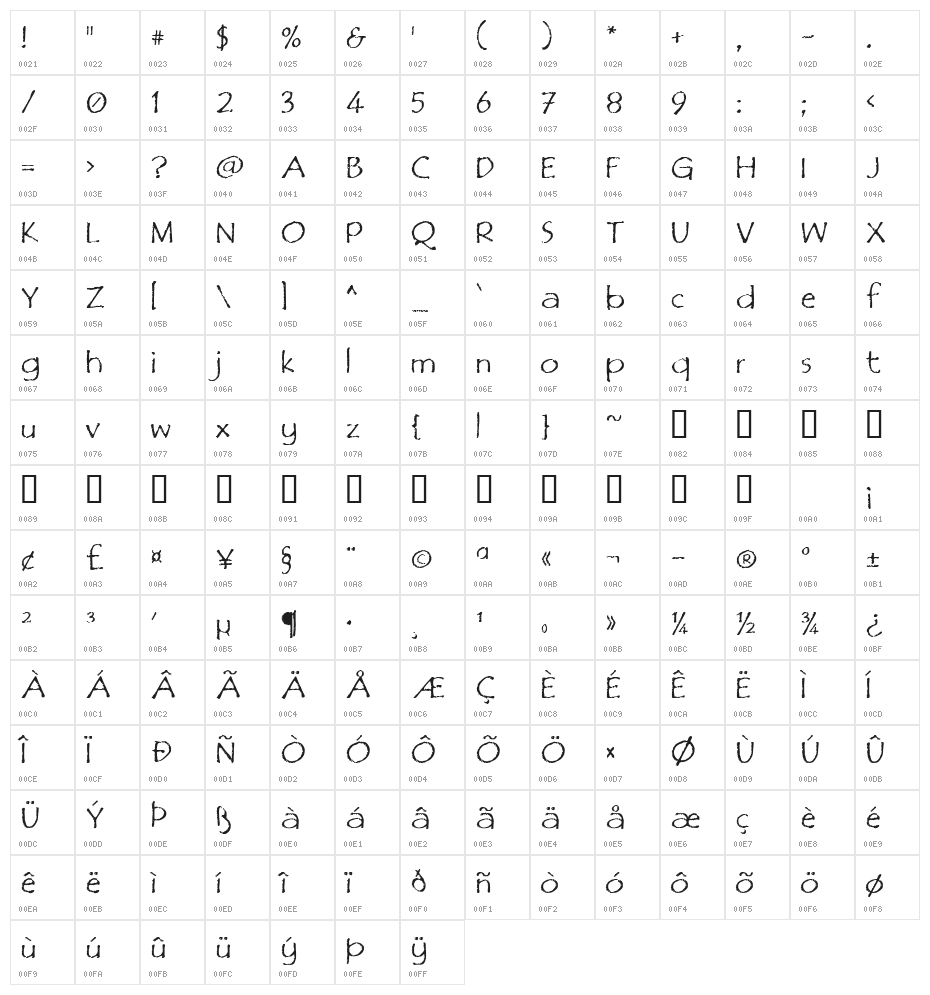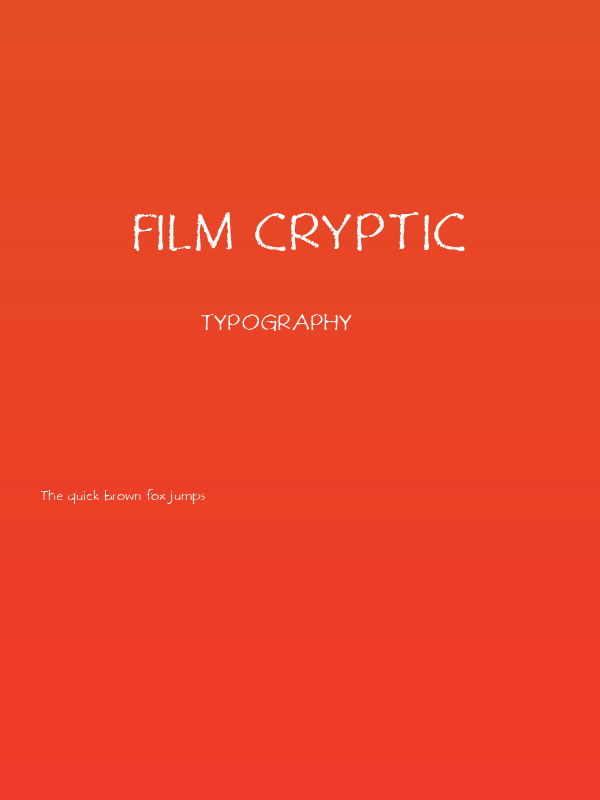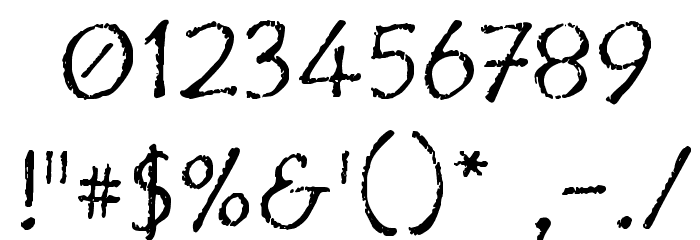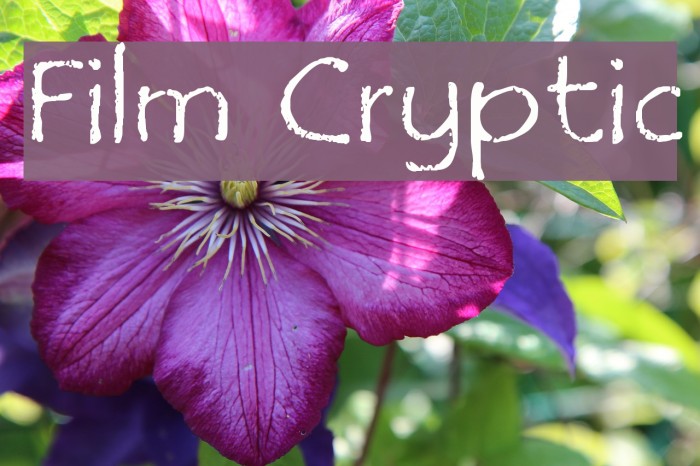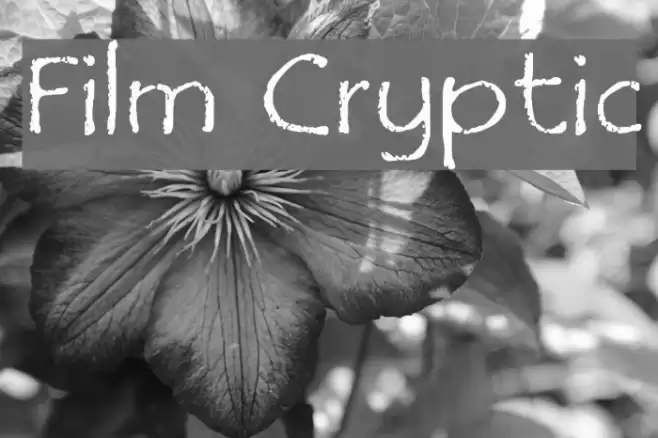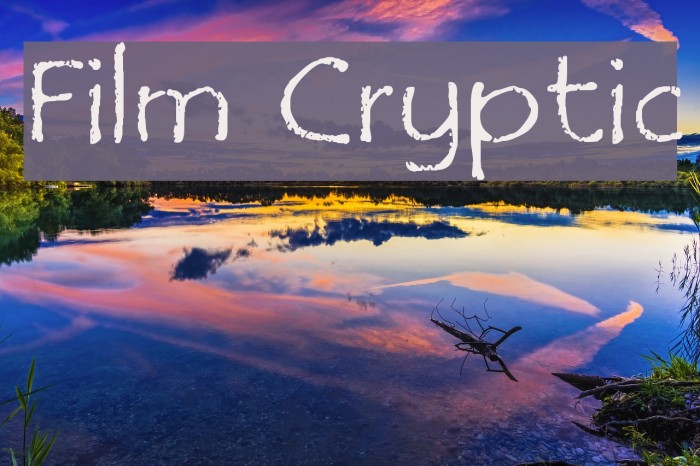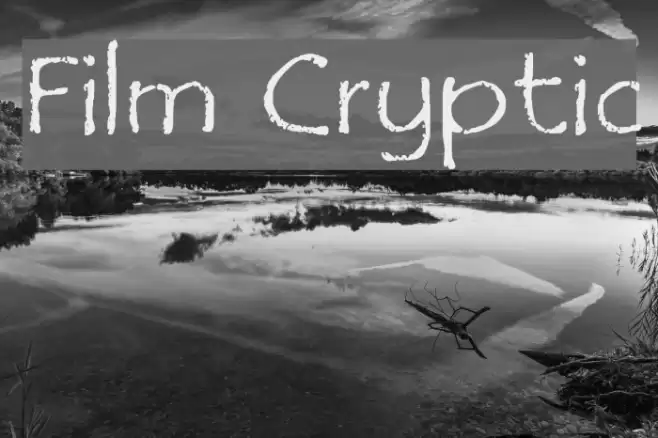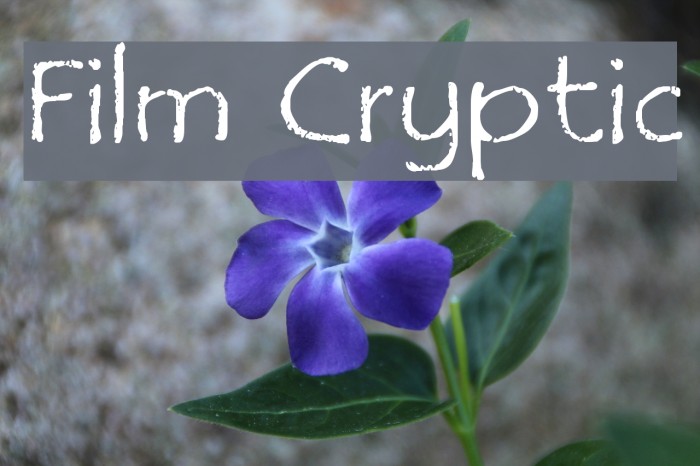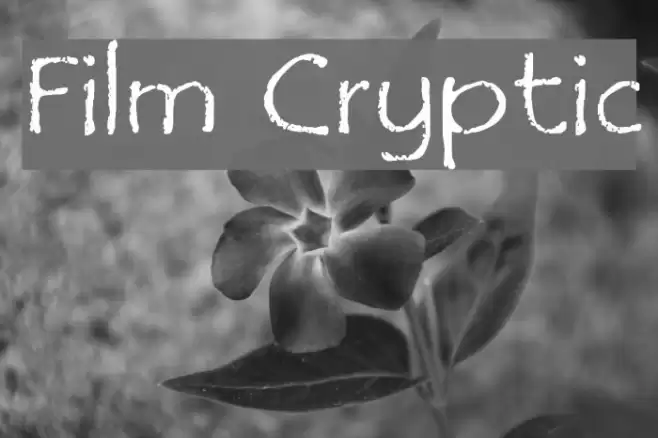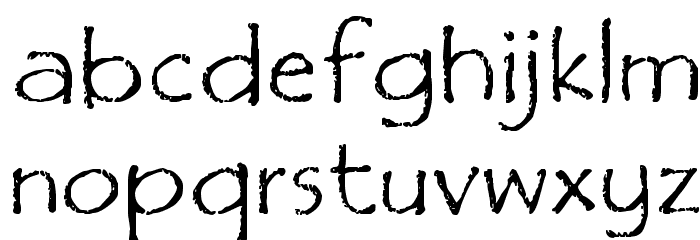
Film Cryptic Font
✎ Distorted Eroded
| Категория | Distorted Eroded |
| Общий стиль | Vintage, Decorative |
| Рекомендуемые проекты | Ideal for movie posters, album covers, mystery novels, or any project requiring a vintage or cryptic aesthetic. |